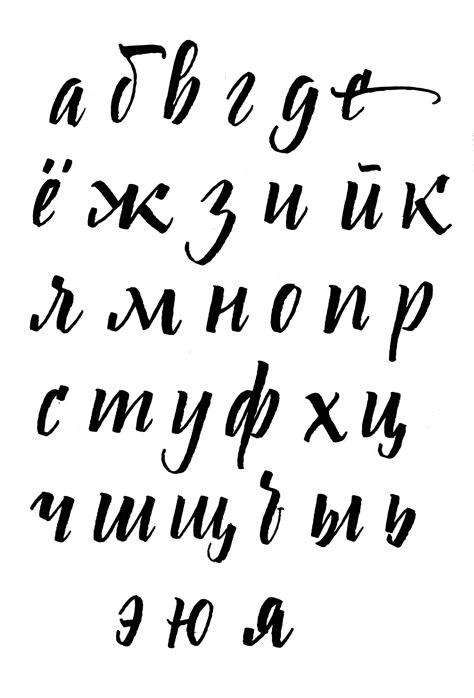
О том, как проходила реформа русского алфавита
Русский алфавит проделал долгий путь от торжественного церковнославянского устава до современного многообразия шрифтов.
Одной из вех на этом пути стала реформа Петра I, в результате которой «буквы переодели в европейскую одежду». В этом году реформе Петра I исполняется 310 лет. О том, как проходила реформа русского алфавита, рассказывает доцент кафедры общего и русского языкознания Института Пушкина Роман Тельпов.
Зачем понадобилась реформа русского алфавита?
По поводу русского алфавита, как и по поводу других преобразований Петра I до сих пор приходится сталкиваться с таким стереотипом, что царь проводил свои реформы исключительно в связи со страстью ко всему заимствованному и иноземному. Это совсем не так. Все его реформы были обусловлены причинами экономического и политического характера. Реформа русской орфографии не является исключением. Главной причиной было стремление приблизить шрифты, использовавшиеся в России к их зарубежным аналогам. Своими начертаниями буквы допетровской кириллицы сильно отличались от букв латинского алфавита, имели много декоративных элементов, что сильно усложняло печатание книг на русском языке.
С развитием науки и образования в России требовалось больше печатных книг, и орфографическая реформа Петра I способствовала развитию печати. Много говорят о том, что реформы Петра грубо меняли русский быт, русскую культуру. На мой взгляд, пример с реформой русского алфавита говорит об обратном – обратите внимание на то, что ни одна буква кириллицы не была полностью заменена своим иноземным аналогом: буквы В, Г, Д и др. сохранили свое начертание даже несмотря на наличие у них латинского эквивалента. Даже в «европейских одеждах» кириллица осталась кириллицей. Необходимо отметить, что переводу кириллицы на гражданский шрифт подвергались только светские книги. Богослужебные книги продолжали печататься по старому образцу. Пример подобного бережного обращения с русским алфавитом нам то, что Петр I всегда оставался русским православным человеком, достаточно бережно относившимся к истинным глубинным основам русской культуры. Император Петр сам был интересной языковой личностью, не лишенной очень своеобразного языкового вкуса, что воплотилось в грубоватой, но по-своему замечательной стилистике его указов.
Как проходило реформирование русской азбуки?
Начало реформам русской азбуки было положено в Амстердаме в 1707 году, когда Петр I приказал составить образец новой русской азбуки и отлить по этому образцу типографский шрифт. Из-за этого новый алфавит называют не только гражданским, но и амстердамским. В 1707 г. новый шрифт изготовил и привёз в Россию мастер Антон Демей. В том же году привезенный из Голландии шрифт отлил в России «словолитец» Михаил Ефремов. В марте 1708 г. шрифтом, отлитым Михаилом Ефремовым, была напечатана книга Геометрiа славенскi sемлемѣрiе иѕдадеся новотiпографским тiсненiем, ставшая первой книгой, напечатанной в России новым гражданским алфавитом, доработкой которого царь занимался лично до 1710 года. Сохранились воспоминания современников о том, как к Петру I присылали образцы новых букв из Москвы в Воронеж, где он в 1709 году руководил строительством русского флота, как тщательно Петр I осматривал их, высказывал свои замечания.
В 1710 году царь повелел составить для него азбуку с «изображением древних и новых письмен славянских печатных и рукописных». Из этой азбуки, содержащей как новые, так и старые буквы Петр лично вычеркнул те, что были на его взгляд лишними. Листы азбуки с правкой, внесенной Петром I, дошли до нашего времени. Также до нашего времени дошел автограф царя на обороте азбуки: «Сими литеры печатать исторические и манифактурныя книги, а которыя подчирнены, тех в вышеписанных книгах не употреблять».
Какие именно буквы были исключены из русского алфавита с реформой Петра I?
Вопрос сложный, потому что на протяжении реформы состав исключенных букв менялся. Первоначально из русского алфавита были исключены буквы ѹ «ук», ѿ «от», ω«омега», ξ «кси», ѱ«пси», ѵ «ижица», ѧ «юс малый». Для обозначения звука [и] стала использоваться буква I без точек. Буква ψ «ферт» сначала была упразднена, заменилась фитою ѳ, но впоследствии та и другая буква были восстановлены с сохранением прежнего распределения.